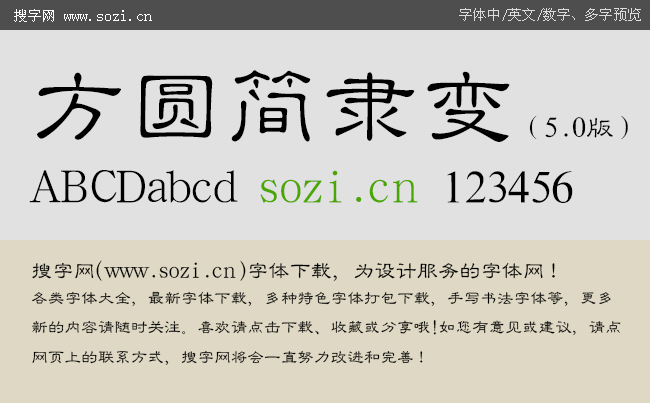
方圓簡(jiǎn)隸變
搜字網(wǎng)提供方圓簡(jiǎn)隸變中文藝術(shù)字體下載,方圓簡(jiǎn)隸變是一款應(yīng)用于設(shè)計(jì)方面的中文簡(jiǎn)體漢字,該字體字體大方工整,整體效果十分出色,可以應(yīng)用于廣告設(shè)計(jì)、名片設(shè)計(jì)、包裝印刷、產(chǎn)品設(shè)計(jì)等應(yīng)用。